Samsung-მა S23 Ultra მოდელის კამერის შესაძლებლობებს ახალი კამპანია მიუძღვნა. სარეკლამო სააგენტო Ogilvy New York-ის მიერ შემუშავებული კამპანია, სახელწოდებით Tiny Type, მსოფლიოს ყველაზე ცნობილ ურბანულ ნაგებობებზე ჩნდება — მათ შორისაა ნიუ-იორკის Times Square, ლონდონის Piccadilly Circus და ტოკიოს Omotesando.
უფრო დეტალურად რომ ვისაუბროთ, ტექნიკურმა გიგანტმა და Ogilvy New York-მა ფართომასშტაბიანი ბილბორდები შექმნეს. ამ ვიზუალებში ტექსტური შეტყობინებები ძალიან მცირე და დამაინტრიგებელია — სმარტფონის კამერის მიახლოების ფუნქციის გარეშე კი ბილბორდზე დატანილი წარწერების სრულად აღქმა შეუძლებელია.
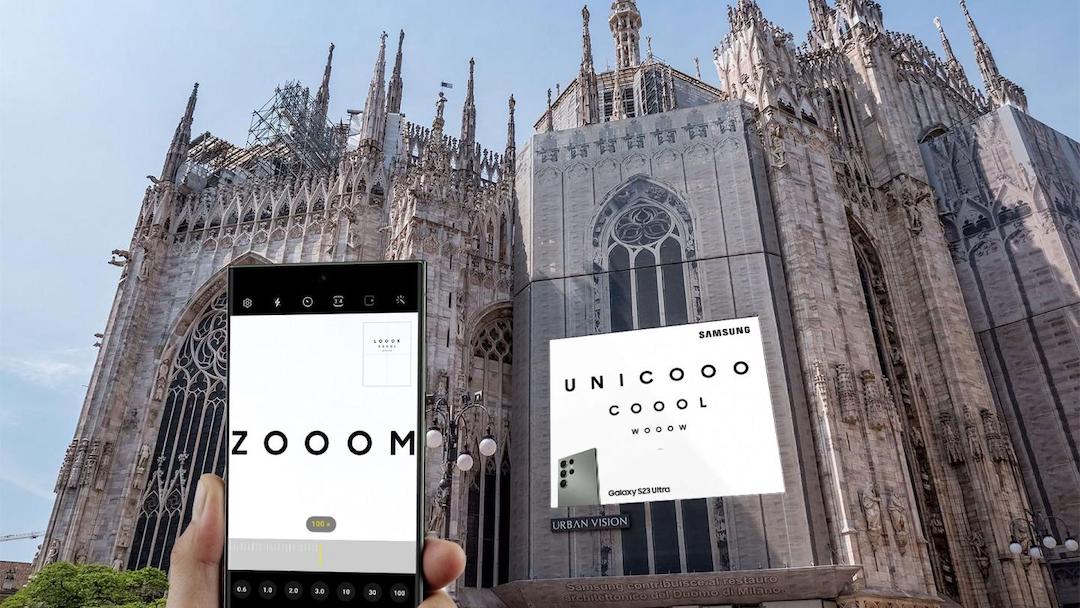
ერთი შეხედვით დაუმთავრებელი წინადადებების მეშვეობით, ელემენტები კრეატიულადაა გადანაწილებული, რათა შეუიარაღებელმა თვალმა სმარტფონის გარეშე უმცირესი ტექსტის წაკითხვა ვერ შეძლოს. რა თქმა უნდა, მთელი იდეა მოწინავე პროდუქტისა და მისი ფუნქციების ეფექტურობის ხაზგასმაა.